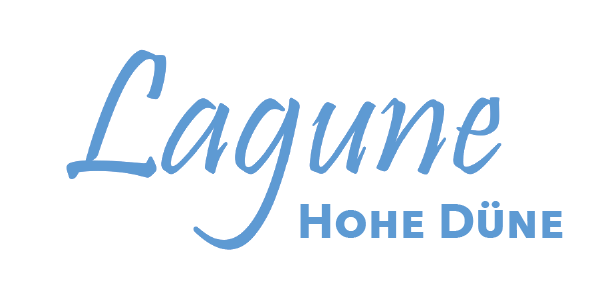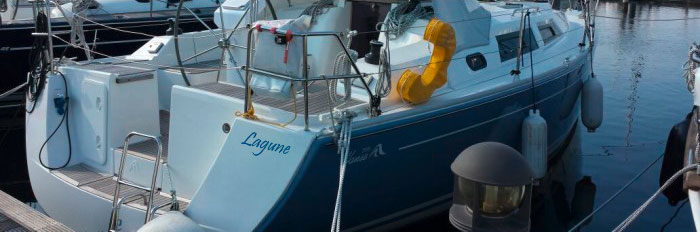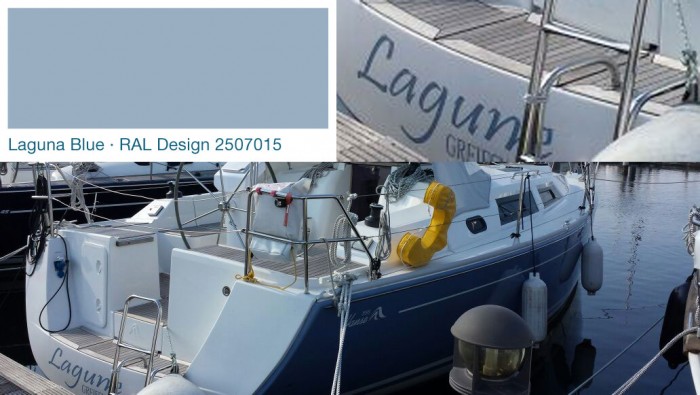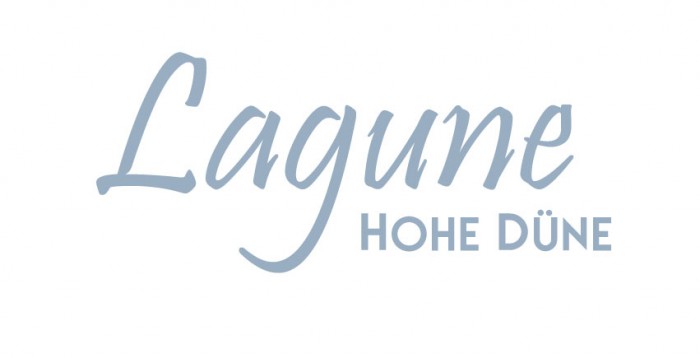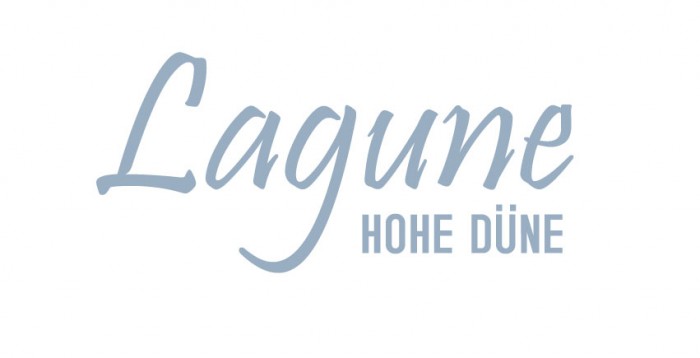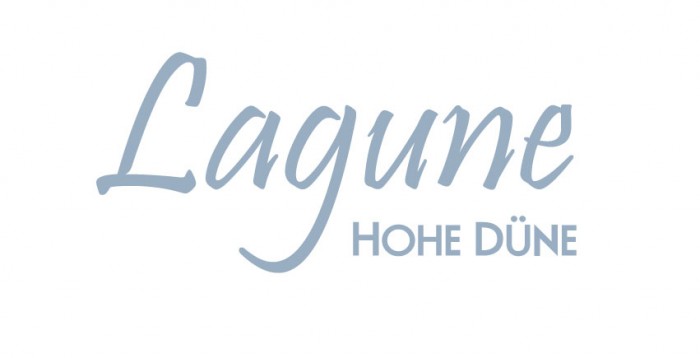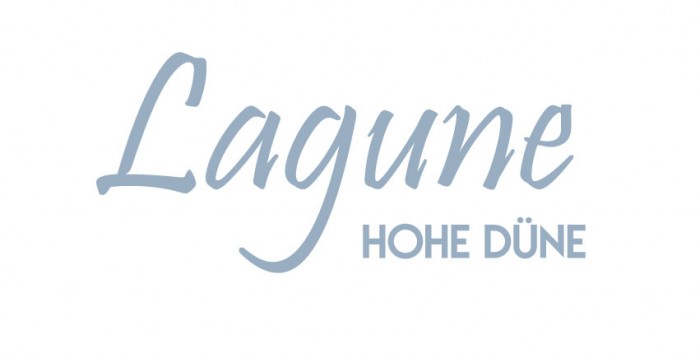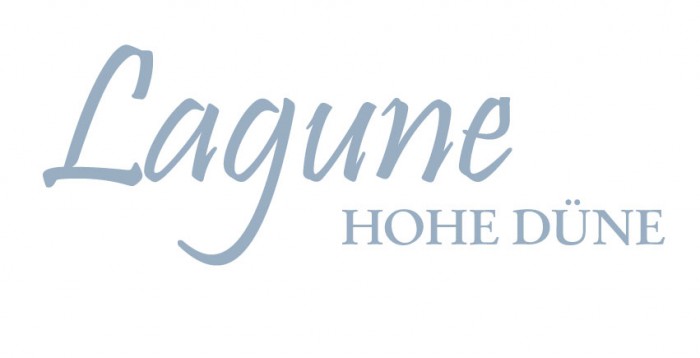
Schriftart unserer Yachtnamens gesucht
nun bin ich ja einmal gespannt, ob jemand von euch diese Schriftart kennt.
Wir haben das Boot zum Ende der Saison gekauft, gerne möchte ich zu Weihnachten nun Cap für die Familien-"Crew" anfertigen lassen.
Alternativ könnte ich in der neuen Saison eine neue Beklebung machen und wäre dadurch frei in der Font Verwendung.
Wie findet Ihr den Schriftzug, habt ihr bessere schönere Ideen?
Ich überlege immer ob ein Schriftzug alleine reicht oder ob ein zusätzliches Bildelement nach nett wäre.
und wie findest du sie und ihre anwendung für das schiff?
Ich würde das entweder dezenter (oder ganz bewusst ganz groß) machen.
Ich glaube, dass es da sogar eine Vorschrift gibt wie groß so eine Schrift sein muss.
Ich freue mich total, dass du den Font gefunden hast, so kann ich alles so lassen!
Im nächsten Jahr muss dann nur der Schriftzug vom Heimathafen in HOHE DÜNE getauscht werden.
Habt ihr dafür eine Empfehlung für eine passende Schrift?
Die aktuelle Schrift "Greifswald" ist auf dem Bild sicher kaum erkennbar.
Baramond Gold? ;-)
Ich würde eine kräftige Geometrische nehmen, aber es gibt auch für jede andere Lösung sicher gute Argumente …
Der ADAC, bei dem wir unser Boot in Deutschland registriert haben (der Verein stellt den Bootsschein aus), gibt eine Mindest-Buchstabenhöhe von 10 cm für den Namen und den Heimathafen vor, wenn ich mich nicht irre. Bei so einem Scriptfont würde ich das vorsichtshalber auf die x-Höhe beziehen. Diese Angabe ist aber ohne Gewähr.
Vielleicht sollte er dann passend zum Heimathafen eine hohe Dünne nehmen …  :party:
vielen Dank für deine Ratschläge mir gefällt deine Herleitung und der Entwurf sehr gut!
Kannst du mir dazu eine Schriftart empfehlen?
Da würde ich erst mal auf Kathrins Rat hören und die Mindesthöhe für die Buchstaben eruieren – eventuell wird das nämlich zu klein, so wie es angelegt habe. Ich hab mir über Bootsbeschriftungen noch keine ernsthaften Gedanken gemacht (dass die im Notfall auf eine gewisse Entfernung lesbar sein können muss, leuchtet mir ein, daran hatte noch überhaupt nicht gedacht. Das spräche übrigens auch gegen ein die wenig kontrastreiche Farbe, die du dir rausgesucht hast.) Bislang war ich froh, nicht aus dem Dinghi gefallen zu sein … :-)
Vielleicht hat jemand der Anwesenden einen guten Rat – vielleicht sogar jemand, der selbst ein Boot (oder waren’s mehrere? ;-) ) sein eigen nennt?  :huhu:
Der Bootsname ist frei wählbar und gestaltbar. Gleiches gilt für den Heimathafen.
Vorgaben gibt es ausschließlich für das Kennzeichen, die da wären
Das Kennzeichen muss
•  in mindestens 10 cm hohen lateinischen Buchstaben und
•  arabischen Ziffern
•  dauerhaft in heller Farbe auf dunklem Grund oder
•  in dunkler Farbe auf hellem Grund
•  außen an beiden Bug- oder Heckseiten oder am Spiegelheck
montiert werden.
Ich habe ein paar Fonts getestet
Ich finde No Movement und Baar Sophia am besten.
Man kann sich da aber verlieren, es wird Zeit, dass das Schiff wieder in Wasser darf! ;-)
wenn versalien (in dem fall passen sie gut) dann brauchen sie mehr luft.
ich würde keine kapitälchen nutzen, besser alle gleich hoch, es macht keinen sinn und sieht unruhig aus.